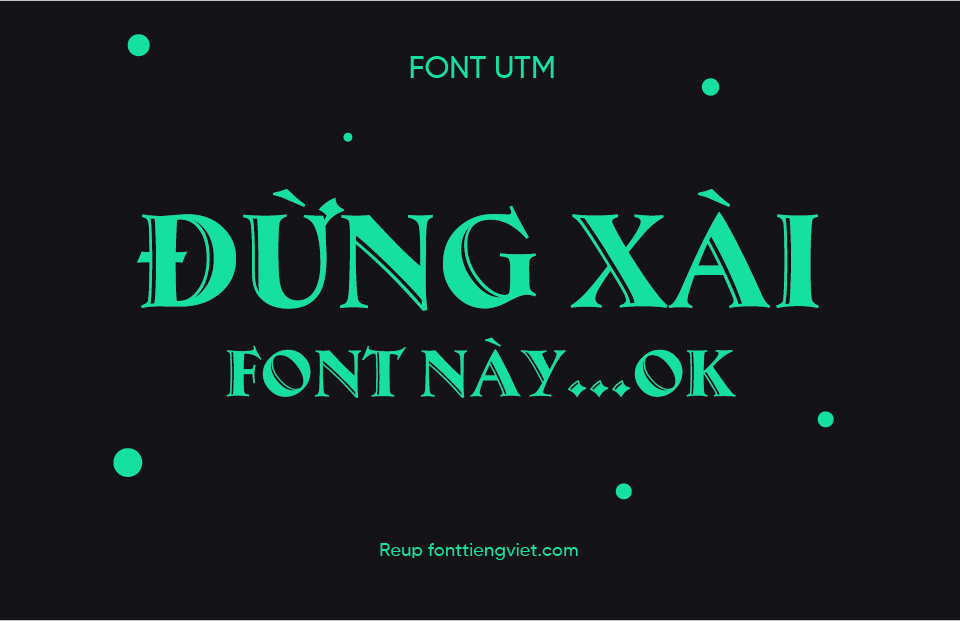
Trong thế giới đồ họa hiện đại, việc tìm kiếm một bộ Font Việt Hóa UTM Ambrose chất lượng luôn là ưu tiên hàng đầu của các nhà thiết kế. Đây là một phông chữ thuộc bộ UTM nổi tiếng, được tinh chỉnh tỉ mỉ để phù hợp với bảng mã Unicode, giúp người dùng Việt Nam dễ dàng sử dụng trong các phần mềm thiết kế chuyên dụng. Khi bạn tìm kiếm Font Miễn Phí để làm nổi bật các dự án cá nhân hay học tập, Ambrose chính là lựa chọn hoàn mỹ nhất.
Đặc điểm nổi bật của Font Việt hóa UTM Ambrose
Phong cách thiết kế sang trọng
Font Việt hóa UTM Ambrose mang trong mình vẻ đẹp cổ điển nhưng không kém phần hiện đại. Với những đường nét thanh mảnh kết hợp cùng các góc bo tròn tinh tế, phông chữ này tạo nên cảm giác nhẹ nhàng, chuyên nghiệp cho mọi văn bản. Nó cực kỳ phù hợp để làm tiêu đề sách, thiệp mời đám cưới hoặc các ấn phẩm truyền thông học đường.
Khả năng ứng dụng đa dạng
Điểm mạnh của bộ font này chính là sự linh hoạt. Bạn có thể sử dụng nó cho các bài thuyết trình slide, làm poster sự kiện hay thậm chí là thiết kế logo thương hiệu. Nhờ việc được việt hóa hoàn thiện, các lỗi dấu câu thường gặp sẽ hoàn toàn biến mất, mang lại sự đồng nhất cho bản thiết kế của bạn.